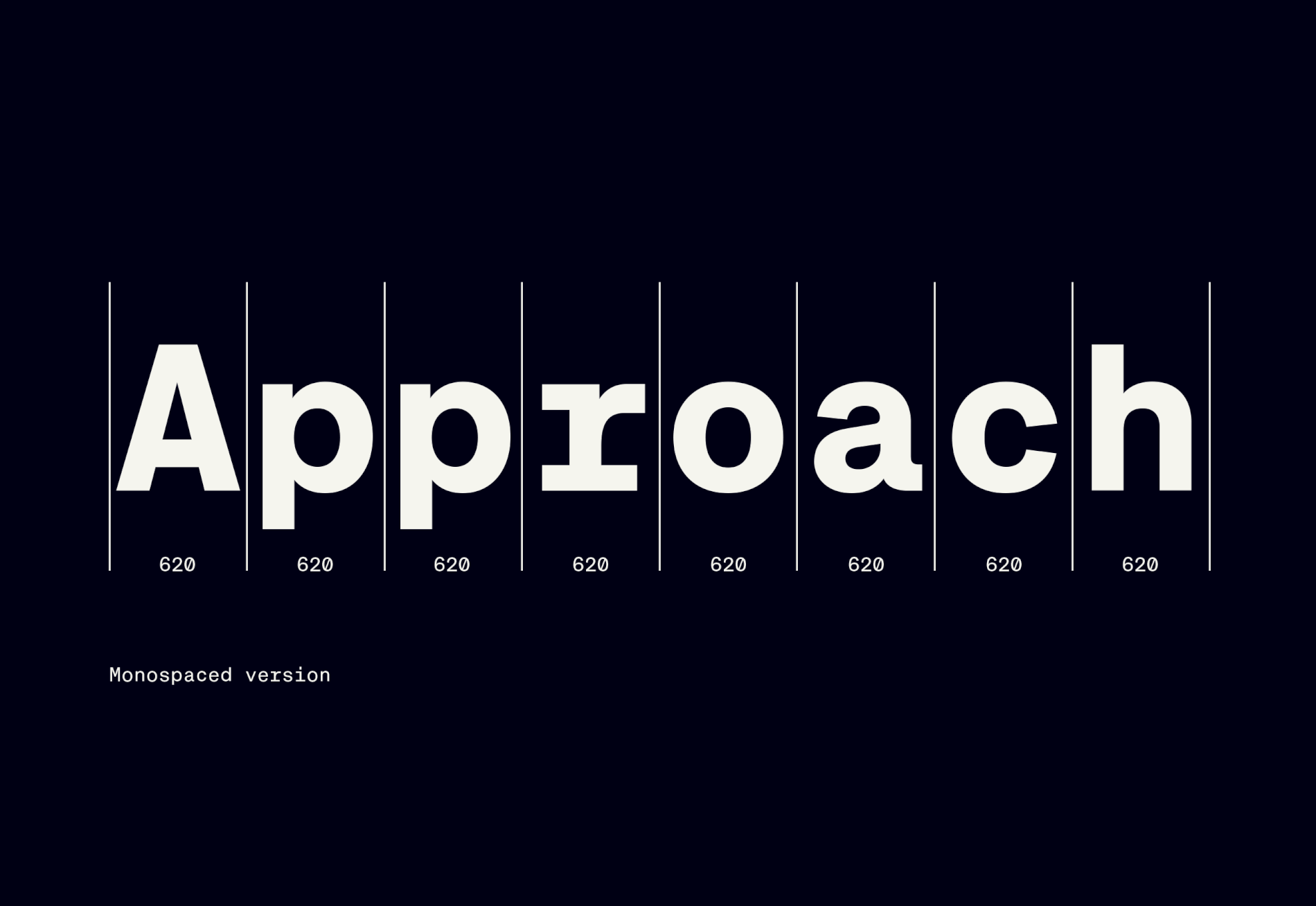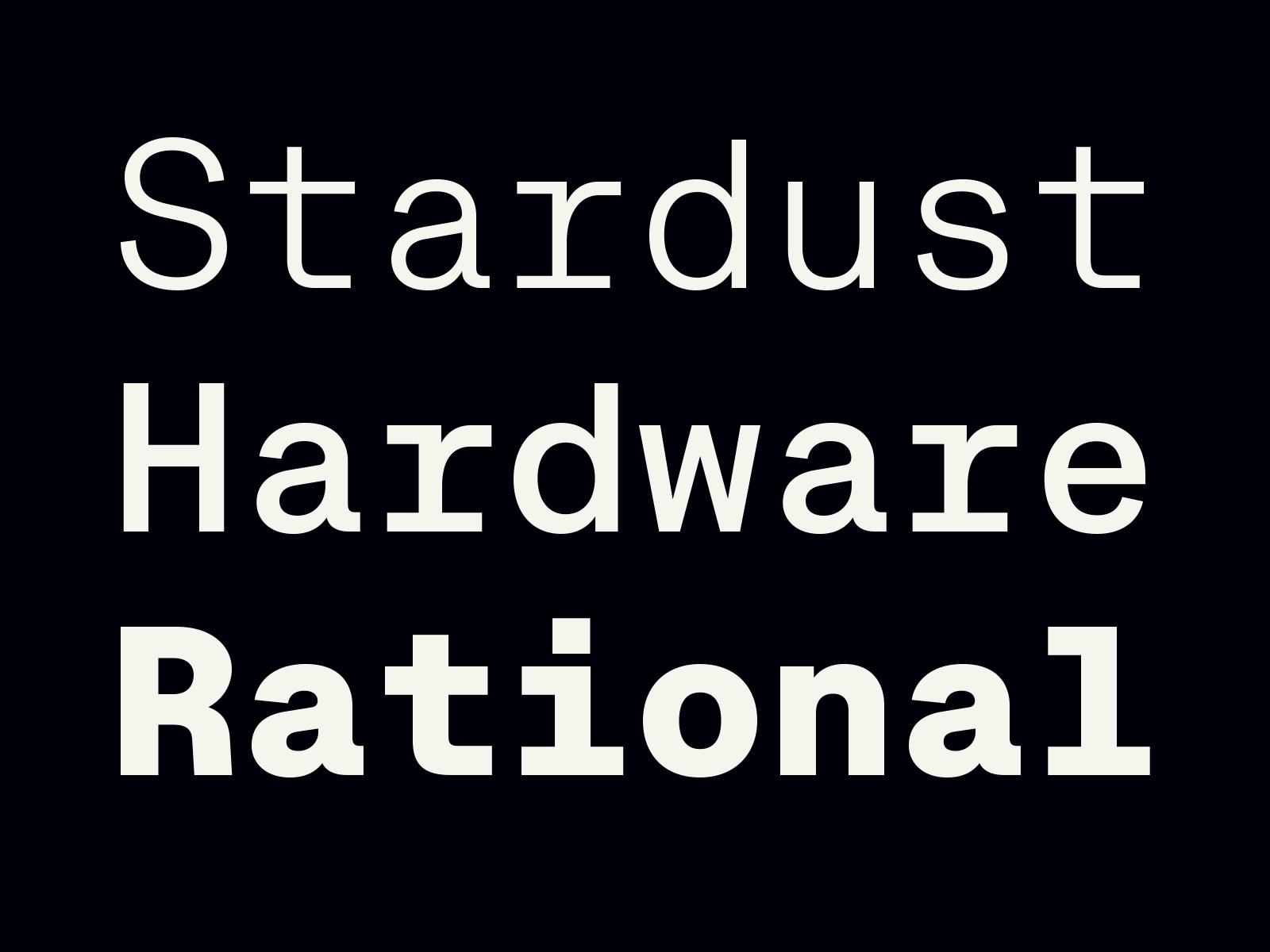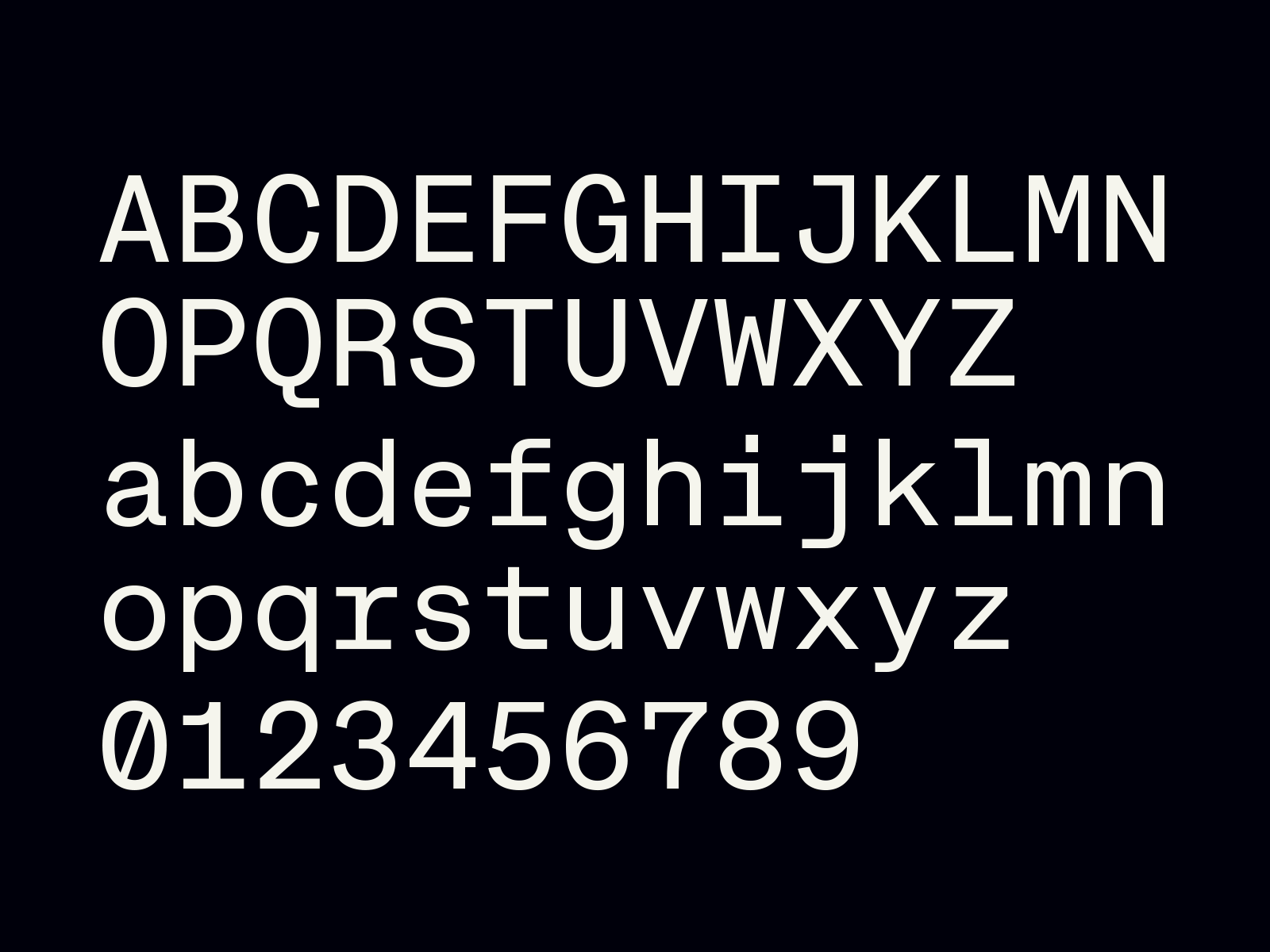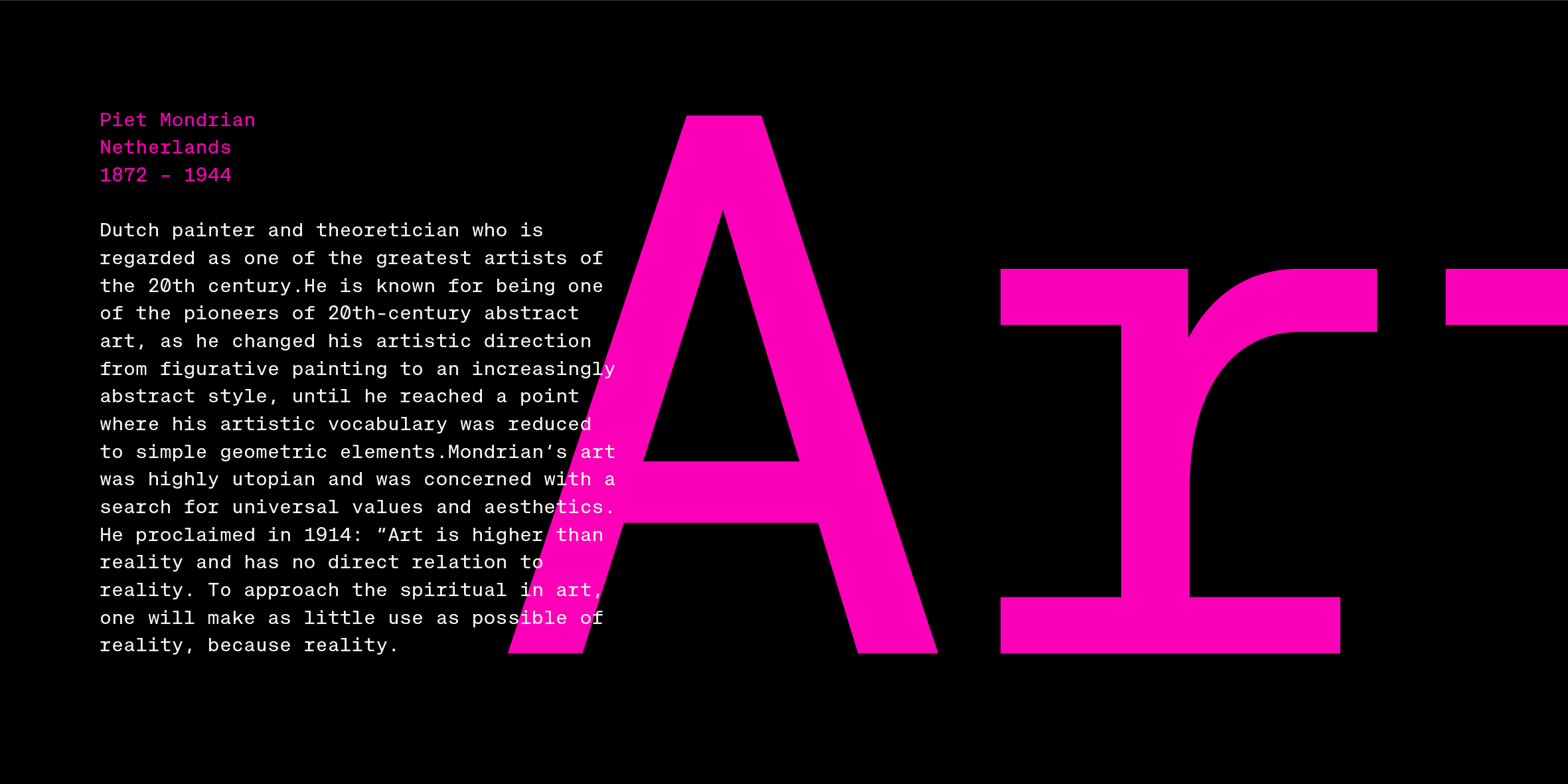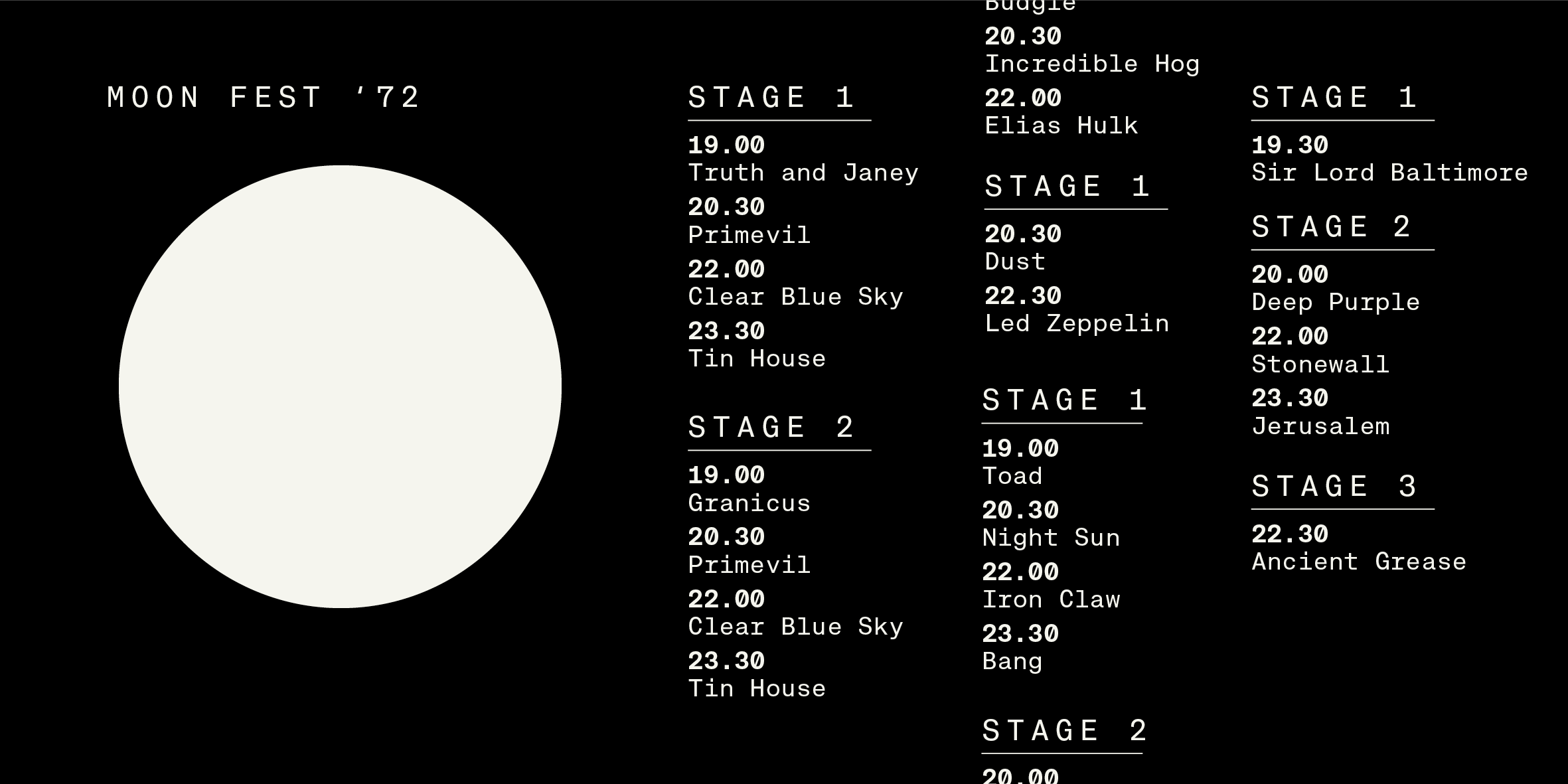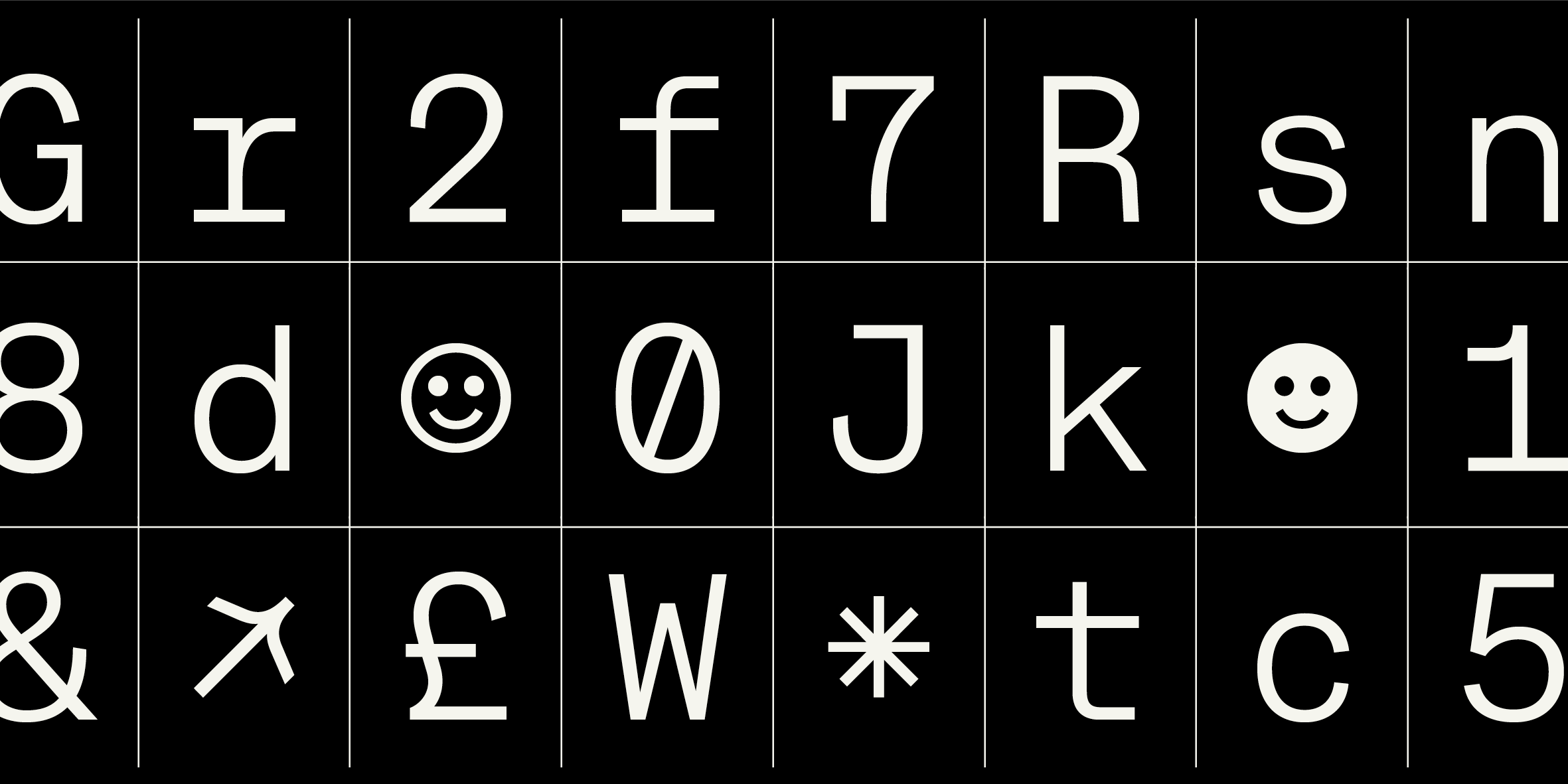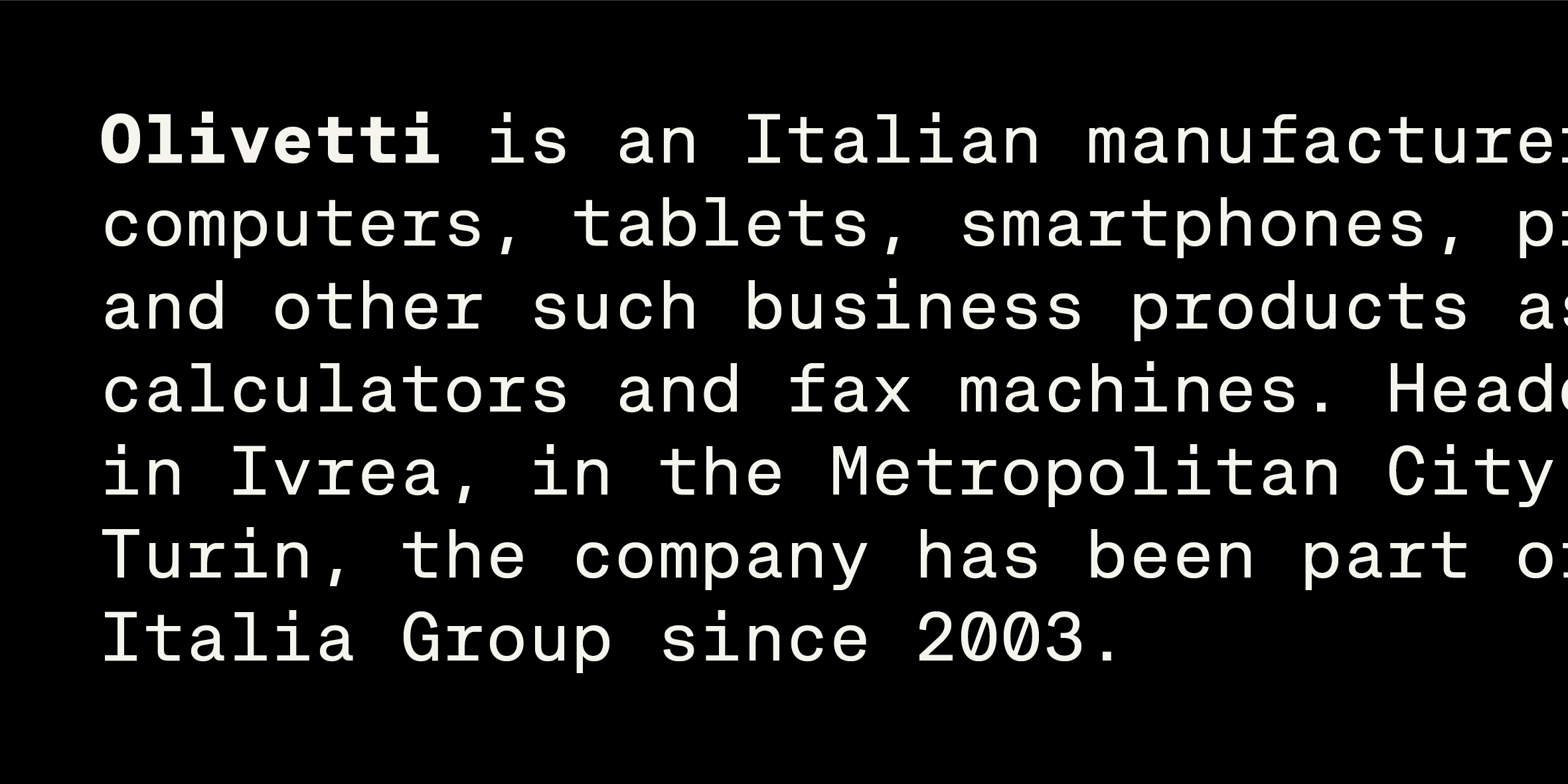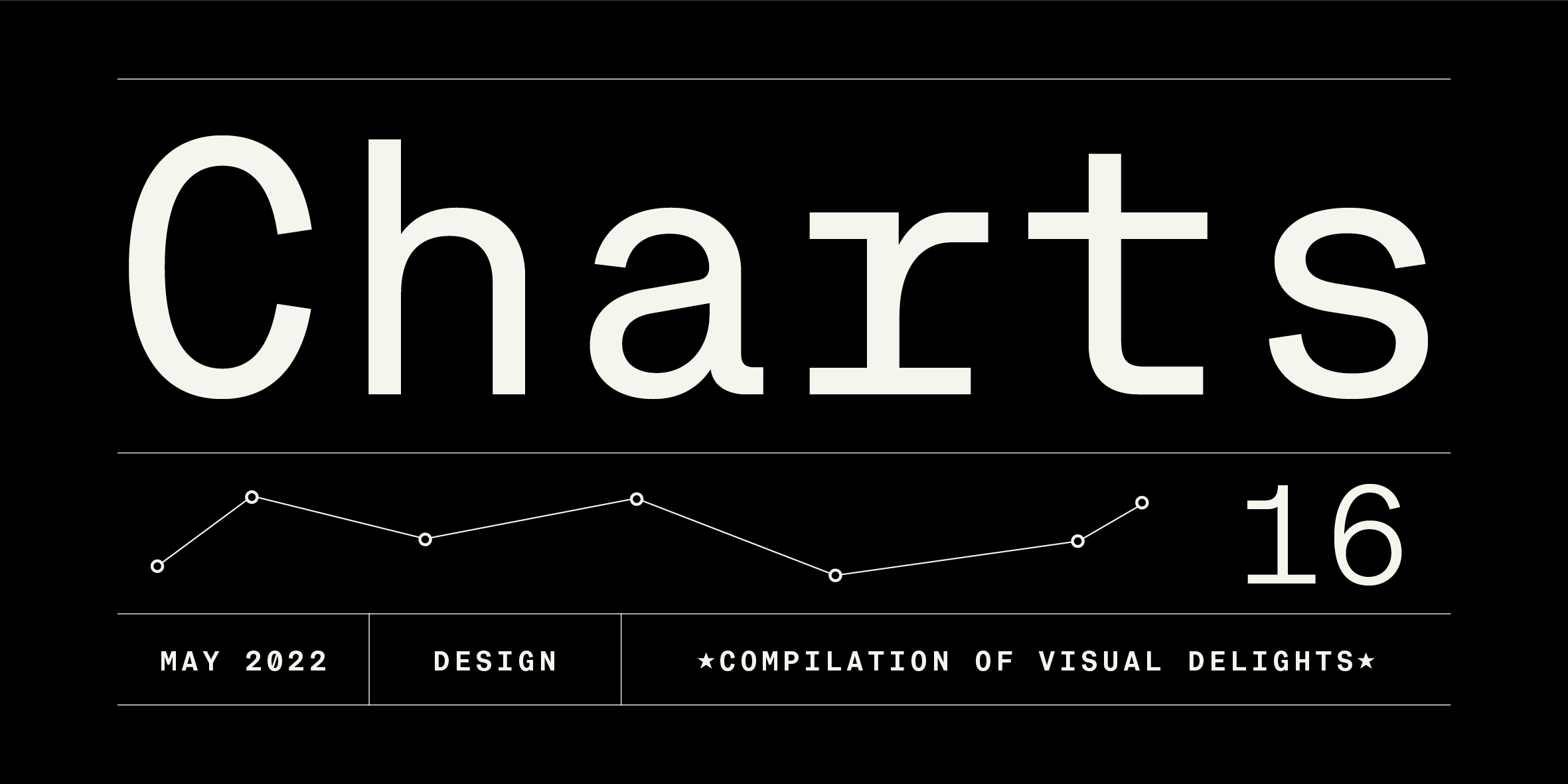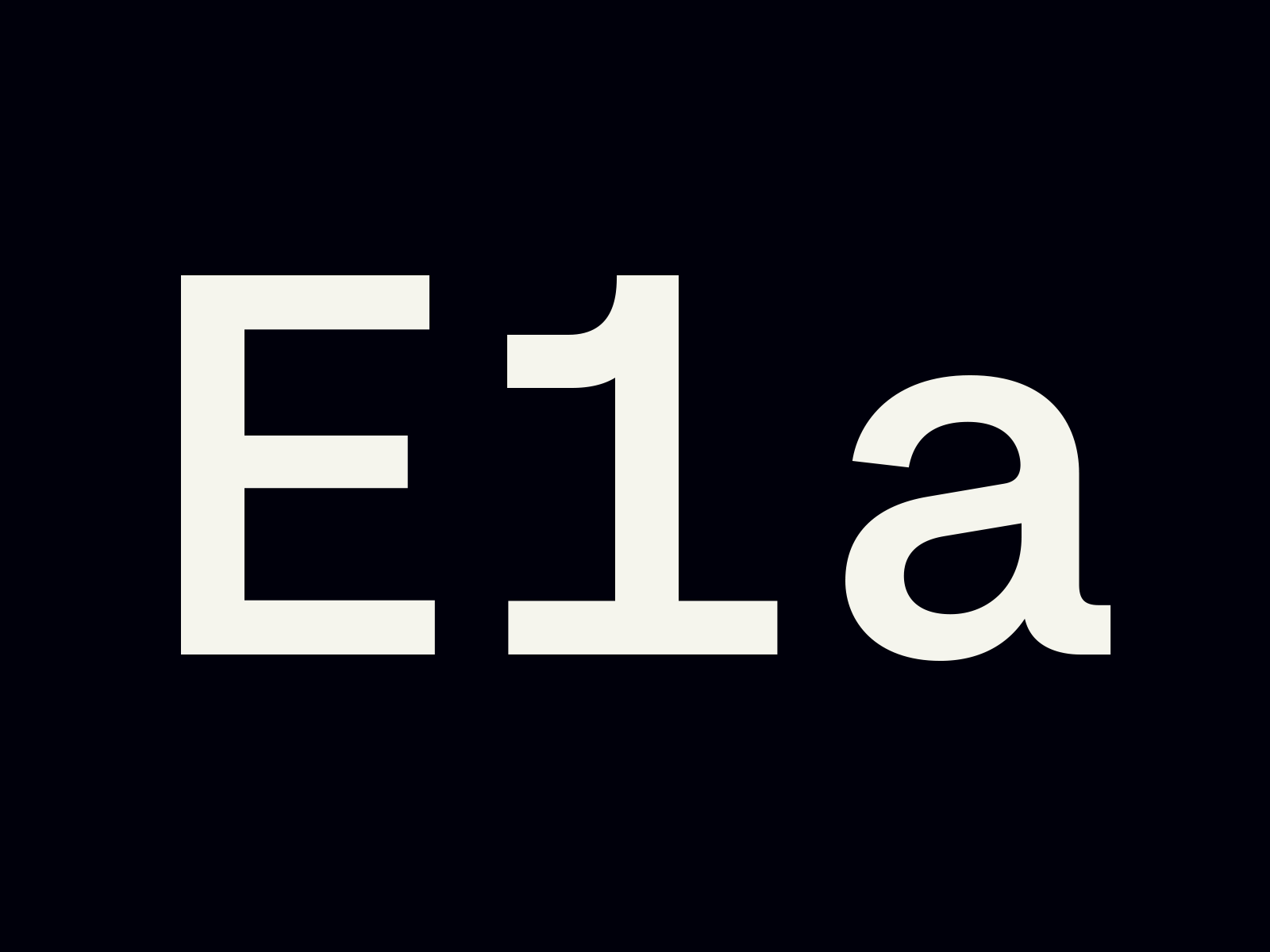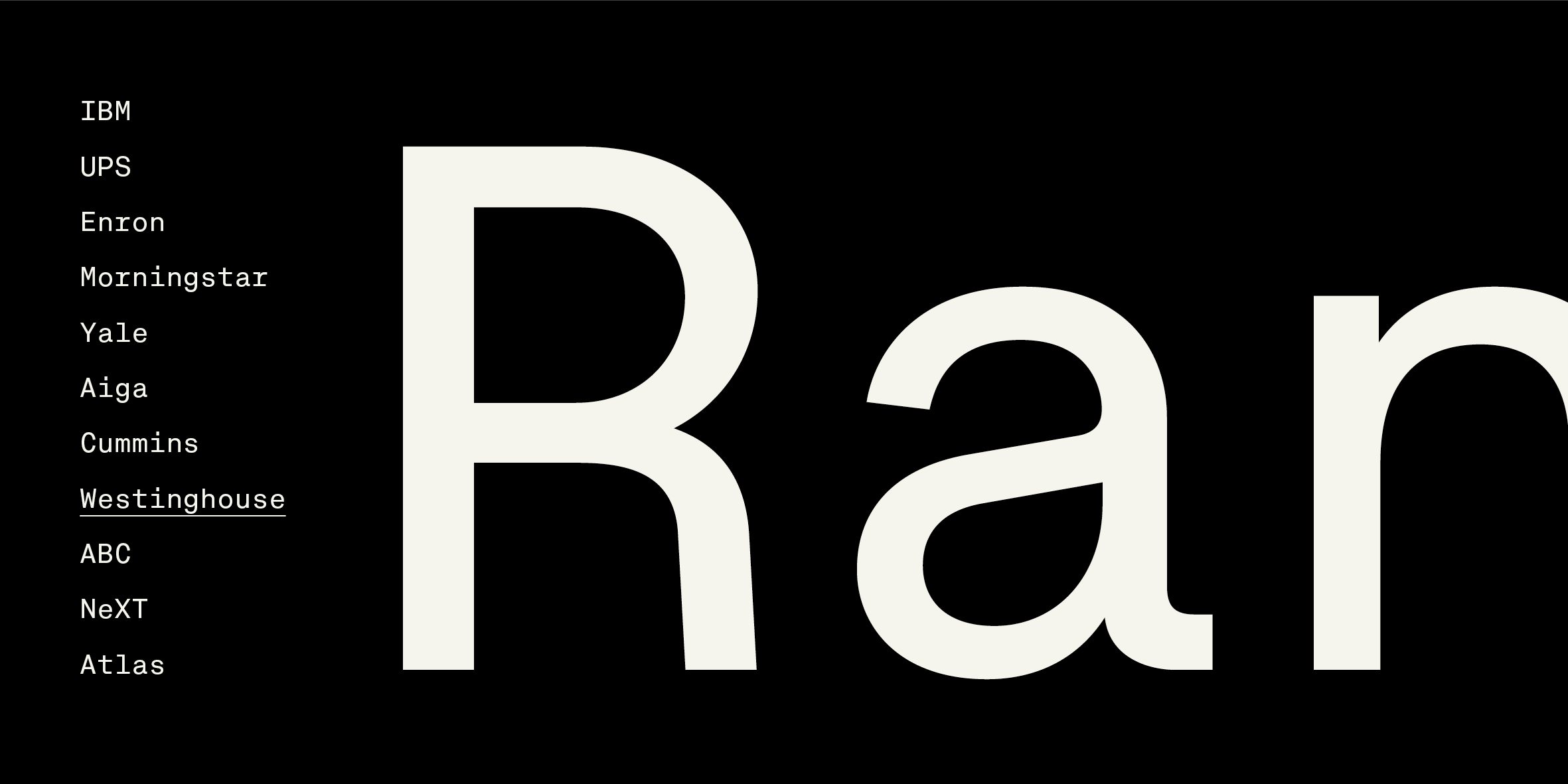
Approach Mono, nueva tipografía!
Pilar Terrón by Pilar Terrón
Approach Mono es la versión de ancho fijo de Approach. Una fuente utilitaria de bajo contraste, un poco mecánica pero con mucho carácter. Esta versión comparte con la original sus características principales, pero tiene una puntuación más prominente y visible. El uso más obvio de un mono sería en tablas, código de programación o textos “work in progress”, pero no solo eso.
Approach Mono es la versión de ancho fijo de Approach.
Approach Mono también puede ser usada en comunicación moderna, aportando una voz aséptica a folletos, publicidad, identidades o cualquier otra pieza gráfica.